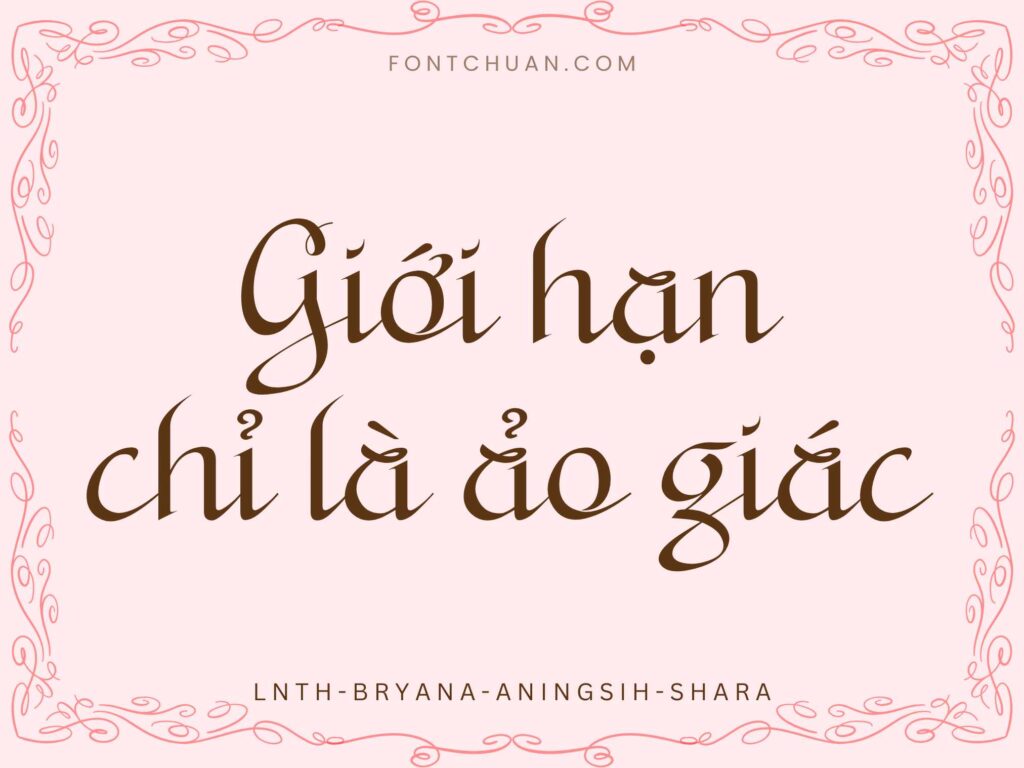
Font LNTH Bryana Aningsih Shara Việt Hóa
Bryana Aningsih Shara là một phông chữ viết tay được thiết kế bởi Situjuh Nazara, mang phong cách thanh lịch và mềm mại. Phông chữ này tạo cảm giác tinh tế và nữ tính, phù hợp cho nhiều dự án thiết kế cần sự duyên dáng và nghệ thuật. Nhờ được Việt hóa bởi LNTH, Bryana Aningsih Shara hỗ trợ đầy đủ các ký tự tiếng Việt, giúp người dùng dễ dàng áp dụng trong các dự án đa ngôn ngữ. Phông chữ này đã được sưu tầm và đăng tải bởi thành viên của Font Chuẩn nhằm đáp ứng nhu cầu đa dạng của cộng đồng thiết kế.
Về đặc điểm thiết kế, Bryana Aningsih Shara có các ký tự được vẽ tỉ mỉ với những đường nét mượt mà, tạo nên phong cách viết tay tự nhiên nhưng không kém phần tinh tế. Phông chữ này đặc biệt phù hợp để sử dụng làm Font chữ ký, cũng như cho các dự án như thiệp mời, bìa sách, poster, logo và các ấn phẩm quảng cáo, giúp truyền tải sự duyên dáng và nghệ thuật. Ngoài ra, Bryana Aningsih Shara cũng thích hợp cho các sự kiện như lễ hội, sinh nhật, Valentine và Trung thu, mang đến không gian ấm áp và lãng mạn. Trong lĩnh vực ngành nghề, phông chữ này được ứng dụng rộng rãi trong quảng cáo, thiết kế thiệp cưới, giáo dục và công nghệ, góp phần tạo điểm nhấn độc đáo và chuyên nghiệp cho các sản phẩm và thương hiệu.